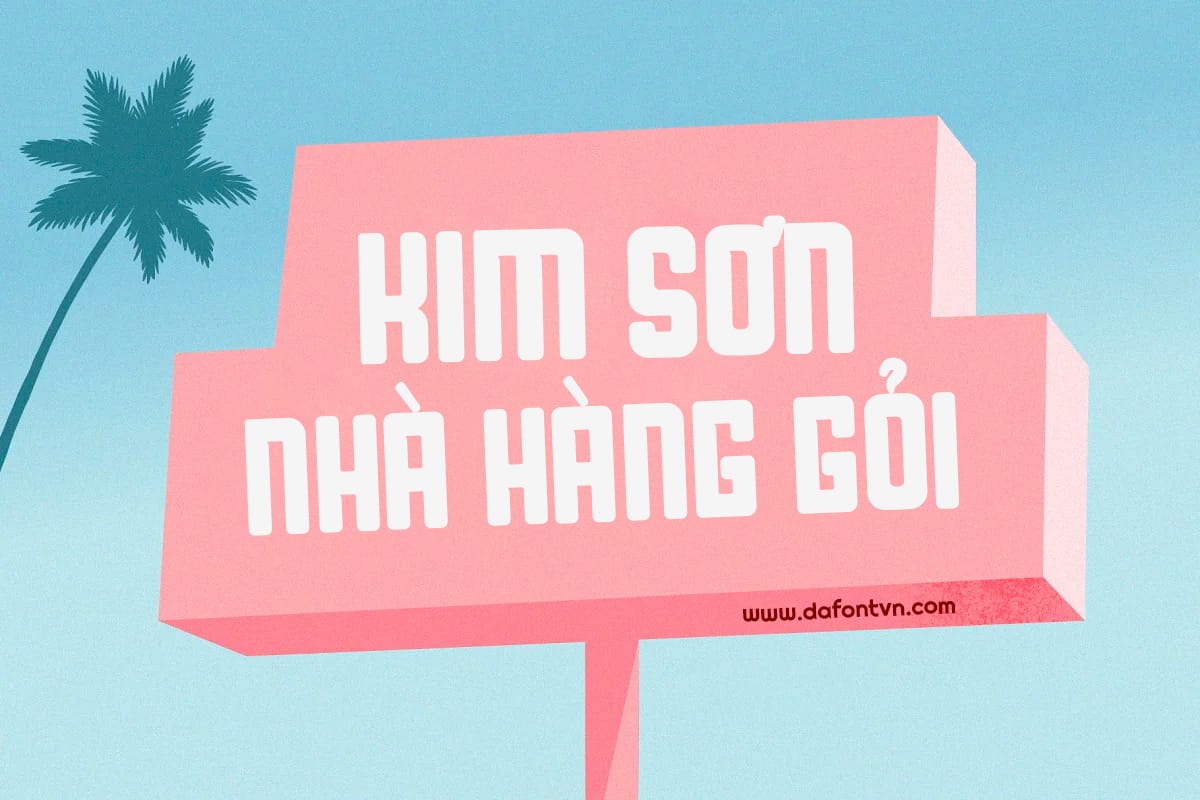
Font iCielBC Downtown Việt hóa miễn phí nằm trong bộ font được Việt hóa và chia sẻ miễn phí bởi iCiel.
Font chữ Downtown là một kiểu lấy cảm hứng từ những điều bình dị hàng ngày ở thành phố đó là màu sắc, đường phố và âm thanh của chúng. Vì vậy đây là một font khá ấn tượng để bạn có thể áp dụng để thiết kế mọi thứ.